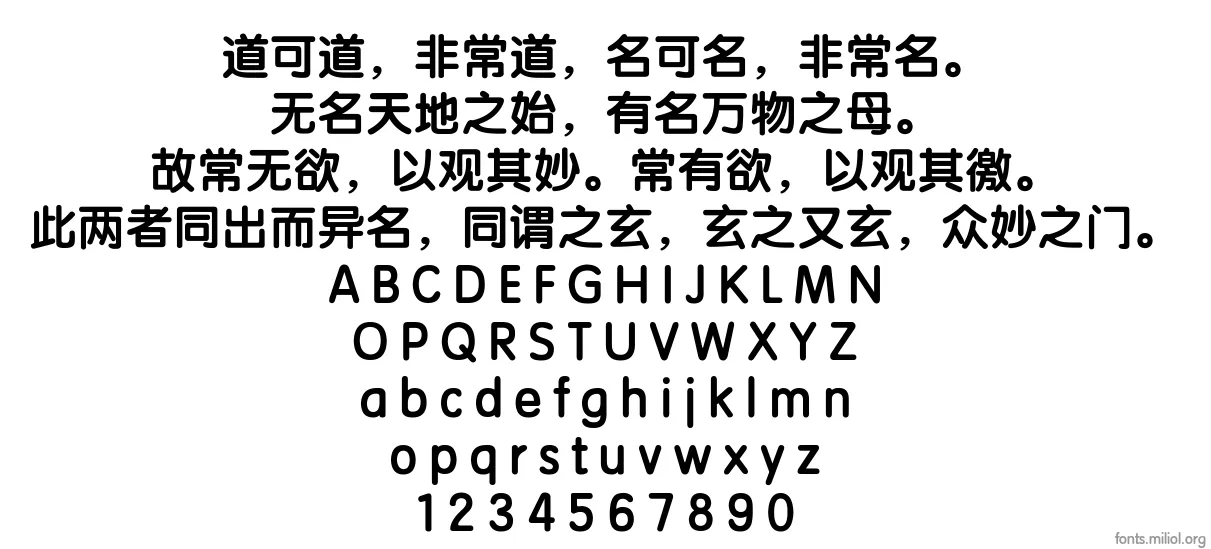
《方正粗圆_GBK字体:设计与应用解析》
方正粗圆_GBK(FZCuYuan-M03)是一款兼具现代感与亲和力的中文字体,其设计融合了圆润笔形与厚重结构,属于方正字库中的经典GBK编码字体。该字体采用标准GB18030-2000字符集,支持繁简中文及多种符号显示,特别适合需要兼容多语言环境的平面设计项目。
从视觉特征来看,粗圆体的笔画末端采用饱满的圆弧处理,字面率较高,在保持清晰辨识度的同时,营造出温暖活泼的视觉氛围。其较粗的笔触重量使文字在屏幕显示和印刷品中都具有出色的可读性,尤其适合标题设计、品牌标识等需要强调视觉冲击力的场景。FZY4K--GBK1-0作为其内部版本代号,体现了方正字库对字体技术参数的标准化管理。
在实际应用中,这款字体常见于商业广告、产品包装及新媒体设计领域。其圆润而不失力度的风格,既能传递友好亲和的品牌调性,又能通过加粗的笔画保持专业感。需要注意的是,使用时应遵守方正字库的授权协议,确保商业应用的合法性。该字体对设计师而言,是平衡个性表达与功能需求的实用工具。